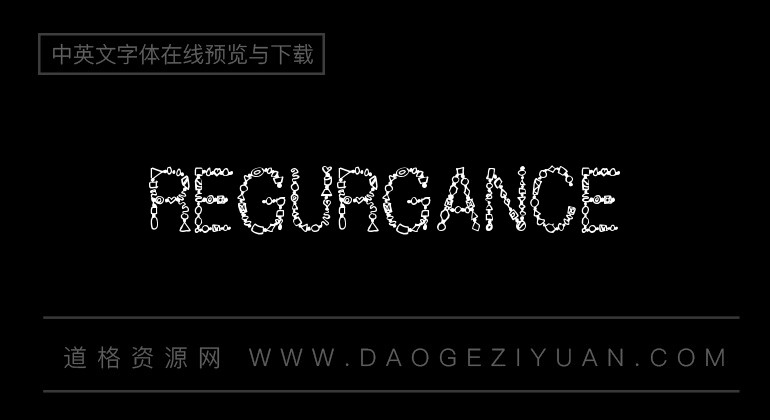
Regurgance 是一款非常有趣的手写字体,它拥有独特的折叠样式,可以提供一种新颖的视觉效果。它的字体特征包括:清晰的笔画、折叠的轮廓、柔和的曲线、深沉的垂直线、活泼的弧度和活跃的水平线。它可以用于创建复杂的设计,也可以用于创作有趣的标题和标签。Regurgance 是一款非常适合用于涂鸦、漫画、艺术等各种设计的字体。内容介绍
Regurgance是一款非常不错的手写艺术字体,具有很好的视觉感,适合于文化类的宣传设计、商业类品牌的广告和产品包装设计以及个性化文字排版等较多场景。